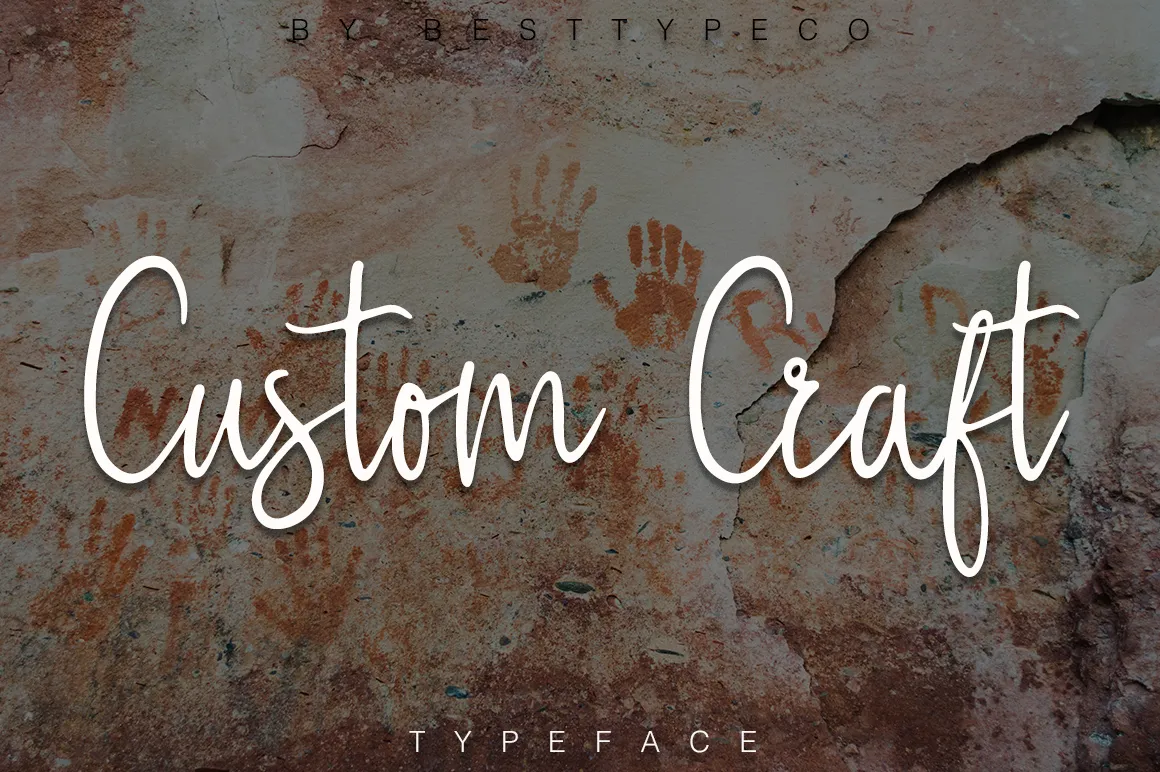
Introduzimos Custom Craft Script Font! Esta fonte foi criada pela 178-MC, uma marca premium disponível na Creativemarket. Agora, por uma breve promoção, você pode baixá-la gratuitamente hoje. Custom Craft é um tipo de letra escrita a mão que se destaca por sua autenticidade e singularidade. A fonte é perfeita para uso em cartões de aniversário, materiais de marca, carteiras empresariais, frases motivacionais, posteres e criações baseadas neles. Ela também se encaixa perfeitamente em sites, materiais de merchandising, embalagens, convites, mensagens pessoais e muito mais. Custom Craft é uma escolha inteligente para qualquer projeto que busque um toque único e autêntico.